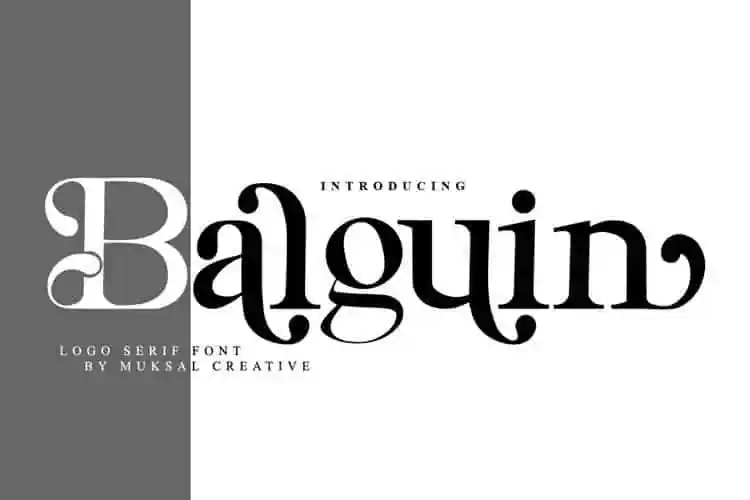
A Balguin Serif Font é uma tipografia serif que combina estilos clássicos dos fonts mais tradicionais com toques minimalistas. Seu resultado final é uma tipografia bela e elegante, complementada por ligaturas que oferecem um toque de sofisticação. Perfeita para logotipos impecáveis, títulos memoráveis e layouts para web, revista fashion e identidade corporativa. Sua aparência notável e sofisticada se destaca ainda mais ao ser escrita toda em maiúsculas, com espaçamento entre as palavras alargado. Além disso, ela impressiona sozinha tanto no capital quanto na minúscula letras. A Balguin Serif Font é uma escolha ideal para quem busca transparência e elegância em um design de fonte.